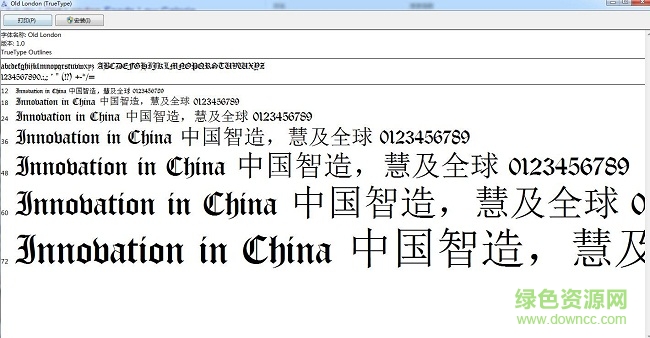
old london字體是一款可以用在Windows系統(tǒng)和Mac上的英文哥特式字體,筆畫(huà)繁復(fù),精美漂亮,還帶有神秘的氣質(zhì),可以用于廣告設(shè)計(jì)或西方古典書(shū)籍的封面設(shè)計(jì),歡迎下載!
它曾是風(fēng)靡歐洲的手寫(xiě)體, 在12世紀(jì)的歐洲,人們用它來(lái)制作商業(yè),法律,語(yǔ)法,歷史等書(shū)籍。直到20世紀(jì),這種字體也還被用于書(shū)寫(xiě)德語(yǔ)。